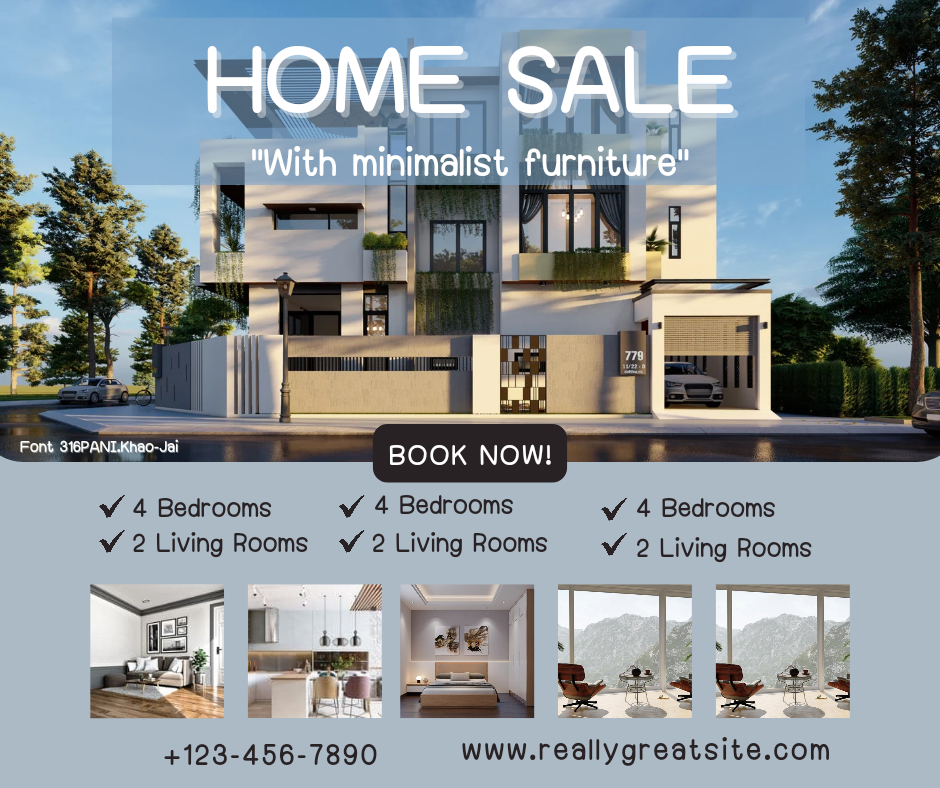
ฟอนต์ เข้าใจ (316PANI.)
PANI.
ฟอนต์ เข้าใจ(316PANI.) แจกฟรี!! ตัวDemo
เข้ากับงานหลากหลายแบบเลยค่ะ
ชุดนี้ดีจริงๆค่ะ อยากแนะนำทุกคนเลยยย
วรรณยุกต์ต่างๆไม่ลอยสูง ไม่ยุ่งยากต่อการใช้งาน
มือใหม่หัดแต่งภาพก็ใช้งานง่ายค่ะ
(แต่งภาพแนะนำยกชุดค่ะ จะได้เลือกน้ำหนักใช้งานได้)
+เพิ่มไฟล์เอียง กึ่งทางการนิดๆ เอียงน้อยกำลังสวยค่ะ
+ไฟล์น่ารักเพิ่มให้อีก สำหรับสาย Cute
ชุดนี้คุ้มค่าต่อการมีลงคลังมากๆเลยค่ะ
--ตัวอย่างการใช้ฟอนต์ใน Canva--